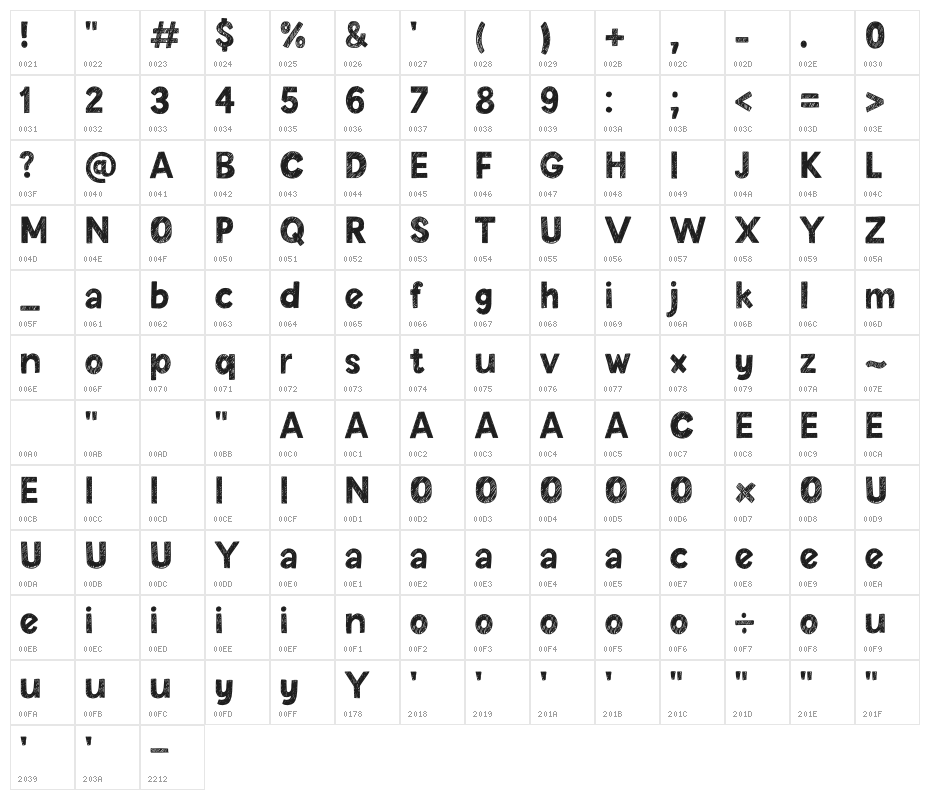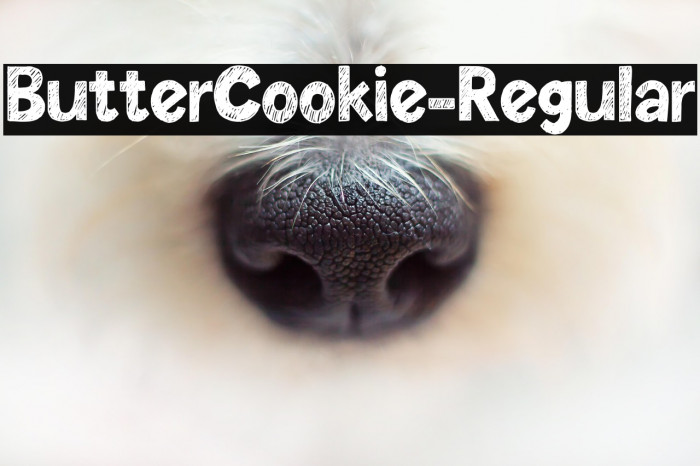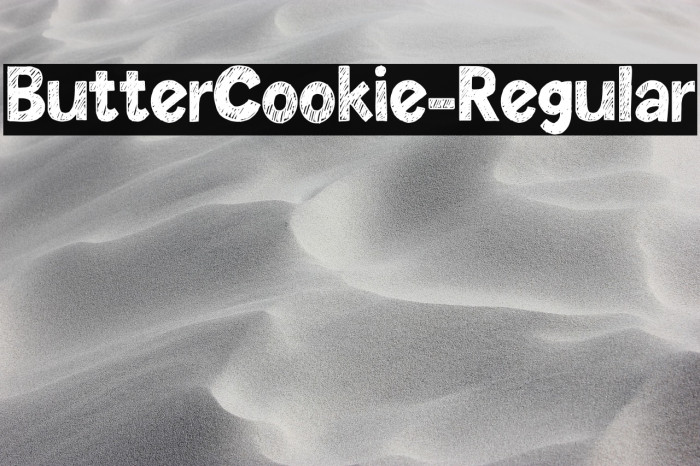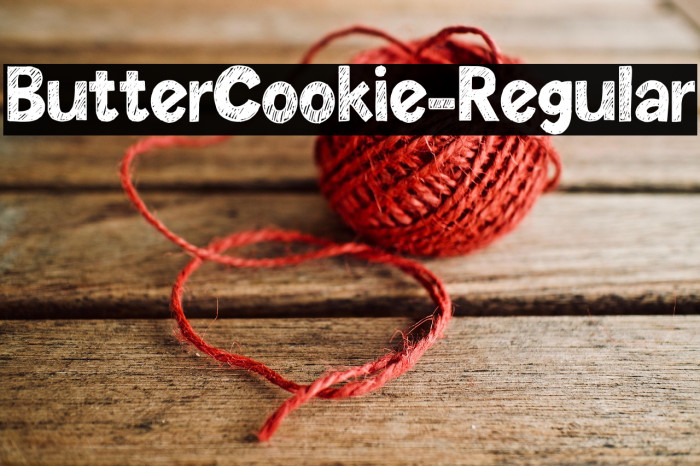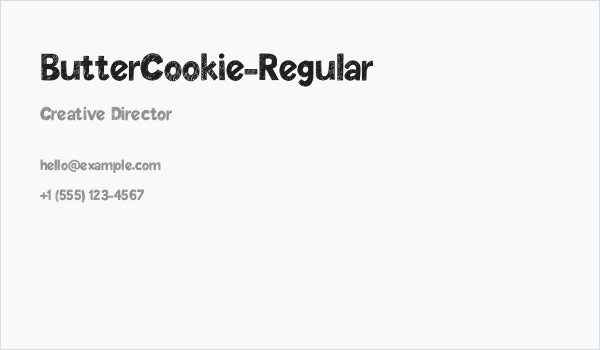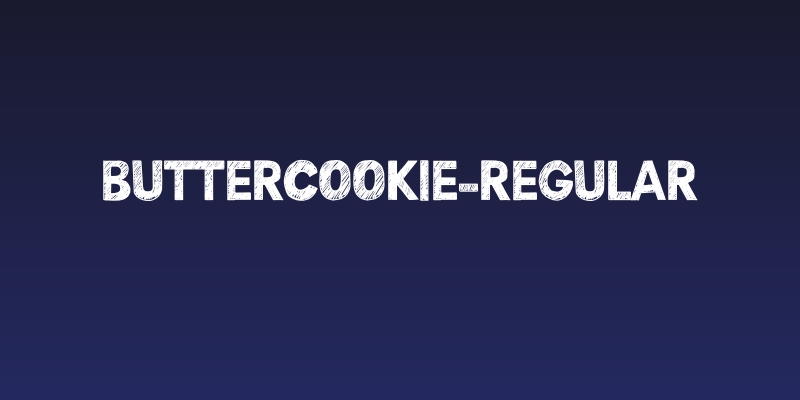
ButterCookie-Regular Font
| Stile generale | Playful, Artistic |
| Progetti proposti | Ideal for children's books, playful branding, creative posters, and artistic invitations. |